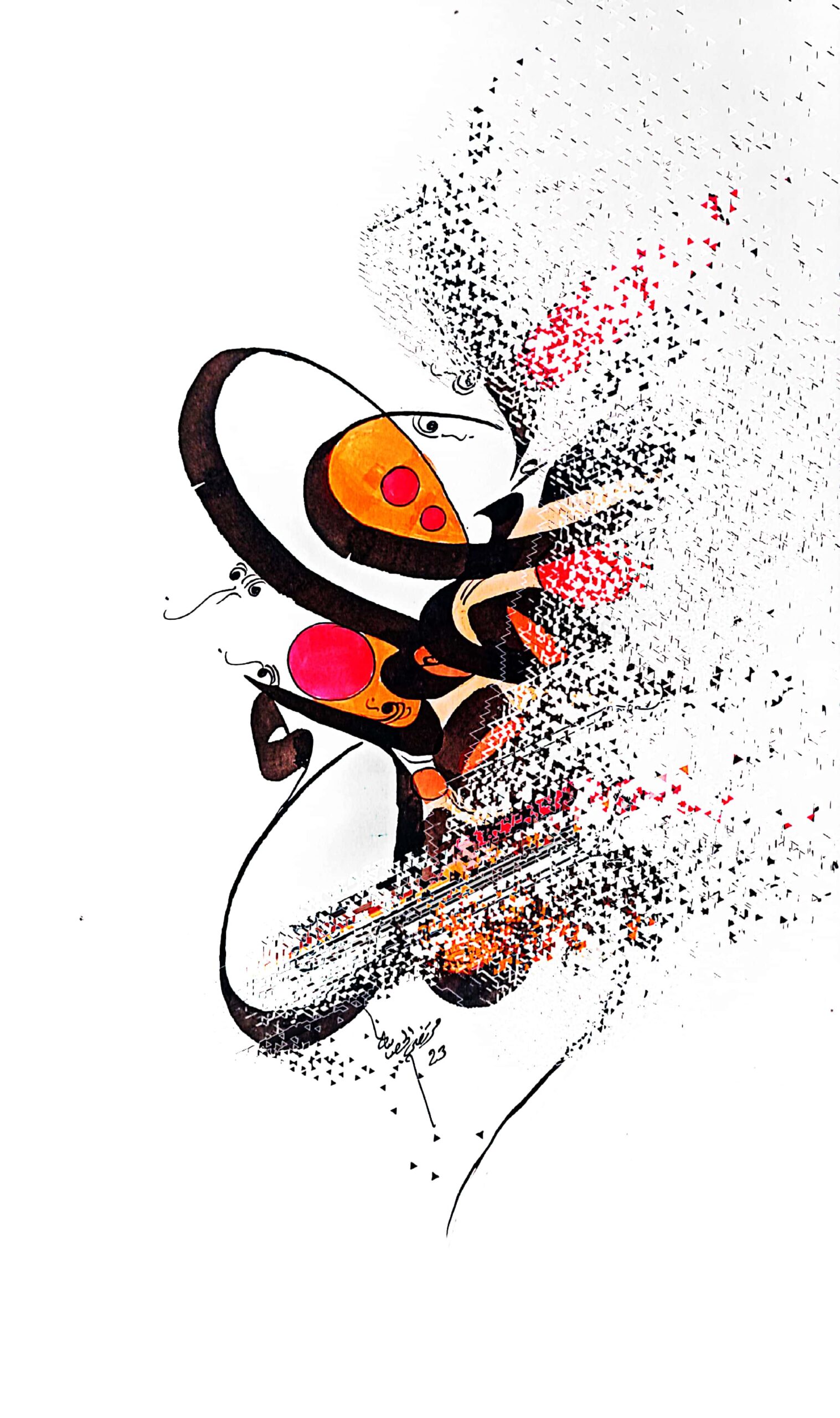
برز الفينيقيين كأول من حول الكتابة من الصورة الرمزية إلى المقطع الصوتي، أي تم استعمال الصور في ترتيب معين لتصبح كلمة أو كلمتين أو جملة، والحروفيون هم أول من حول الحروف إلى صور، فلم يعد الحرف دالاً بحكم صلته بحروف أخرى، كما لم يتم رسمه كاملاً في كثير من الأحيان ، بل اكتفى الفنان بتضخيم مساحة الحرف وتفكيكه ليتحول إلى عنصر تشكيلي، يتم توليفه داخل العمل الفني ” من هنا فإن الكشف عن أهميته ( كبعد)وليس (كموضوع) يصبح بالتالي هو بيت القصيد، وذلك لأن القوام الحقيقي للحرف هو الحركة والاتجاه، فإن أمكن ظهوره كشكل ما، كمساحة فإن بيئته الأساسية هو الخط أي أزل البعدين”[1]، أجل فهو كخط لا ينفك أن يكون أسير الطول والعرض، لكن تلويناته المتحررة من كل نظام، تكون عالماً شعرياً صرفاً، نتيجة انسياب أعداد مهولة للحروف، تؤلف مع بعضها قصيدة بصرية ذات مضامين جليلة.
إن التجربة ليس لها حد أبداً، ولن تكتمل ولن تأتي بالجديد، لأن أفق التصورات مرتبط بما هو محدود ومعروف مسبقاً ، غير أن تمثلات الحرف تبدل آلية التظاهر في كل مرة يتم استخدام جزء منه أو بديل عنه، مايسوغ لقبول جدلية النظام والمخاطرة، حيث يشكل القبول، الشرط نفسه للمخاطرة التي لاتتحقق دون أن تضع النظام موضع التساؤل في الأخير، نظام تعبيري حديث ومعاصر آفاقه حرة.
بالرغم من أن “نجا المهداوي” يُصنف من الحروفيين إلا أننا لا نكاد تمييز حرفاً عربياً واحداً في أعماله. فأسلوبه يعتمد أثر الحرف وليس الحرف. فلو تمعنت في الأشكال التي يرسمها تجدها عبارة عن تخطيطات تكاد تقترب من رسم الحرف ولكنها تمر بانسياب أنيق دون أن تكوّن أي حرف معروف وهي توحي بالتشكيلات الحروفية ولكنها ليست حروف مكتوبة.
لا يندرج الانمحاء الدلالي في الحروفية العربية ضمن منطق نفي الشكل أو المعنى، بل يُفهم بوصفه توجه أو نهج جمالي واعٍ، يعيد صياغة الموروث الزخرفي الخطي من مقروء إلى بحث بصري لايطلب القراءة بل الرؤية، وينقل مجالات التأويل من الدلالة اللغوية، المغلقة حول المعنى إلى الدلالة التشكيلية المفتوحة. فحين يُنزَع الحرف من سياقه أو يجرد من شكله المتعارف عليه باختزاله في ترددات خطية فقط ، ليفقد وظيفته الإحالية المباشرة من أجل اكتساب جمالية جديدة نابعة من حضوره المادي، يكون قد تحول إلى اللاحرف اللغوي المعروف بالاحتفاظ: بخطه، امتداده، انكساره، إيقاعه، وثقله داخل المجال البصري. هنا يصبح الحرف المجرد من خصائصه حاملًا لطاقة رمزية وروحية، تتجاوز المعنى المعجمي نحو أفق تأملي يتقاطع مع مفاهيم الصمت، الغياب، والأثر. ومن هذا المنظور، يشتغل الانمحاء الدلالي كفعل انزياحي، يُحرّر الحرف من وظيفته التواصلية ليعيد إدماجه في نظام تواصلي آخر أي ضمن نظام جمالي مستقل، حيث يتأسس المعنى على مستوى الحسّ والبصر والحدس.
فهم “ألبير كامي” العملية الابداعية على أساس أنها تَقَبُل ثم تمرد، يوافقه على ذلك وليم جيمس برأيه” علينا أن نحتفظ بنوافذ الذهن مفتوحة، أي أن نقاوم الآراء مهما كانت سديدة ونتمرد على المعتقدات مهما كانت صحيحة، شريطة أن لا تكون المقاومة للمقاومة نفسها ولا يكون التمرد للتمرد نفسه، بقدر مايكون حافزاً على متابعة البحث ومجالاً للاقتراب أكثر من الحقيقة”[3]